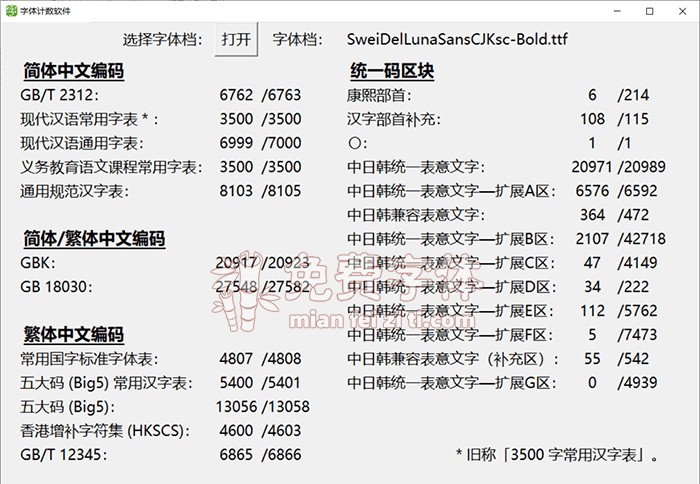
狮尾福音黑体:Max造字 改造思源黑体增加三角形和拔脚免费商用字体资讯
狮尾福音黑体基于思源黑体的笔触增加三角形和拔脚改造,更加简明现代化的字体。支援简体中文、繁体中文、韩文与日文;可以免费商用,欢迎大家自由应用、自由优化、自由改作!
狮尾福音黑体的特色是,「一」字的开头和结尾笔触由平头增加一个小小的三角形。